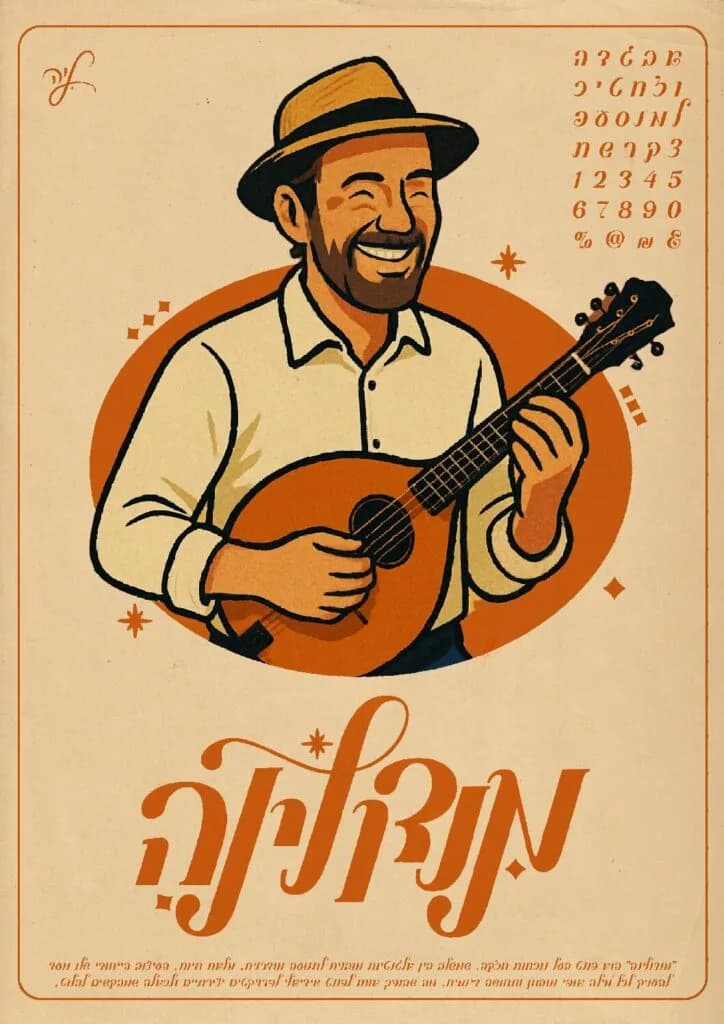
מנדּולינָה טיפוגרפיה דינמית עם אופי ייחודי - "מנדולינה" הוא פונט בעל נוכחות חזקה, שמשלב בין אלגנטיות מובנית לתנועה מודרנית, מלאת חיות. העיצוב הייחודי שלו נועד להעניק לכל מילה אופי מובחן ותחושה דינמית, מה שהופך אותו לפונט אידיאלי לפרויקטים יצירתיים ולכאלה שמבקשים לבלוט. הוא מתאים במיוחד לכותרות ולשמות מותגים שרוצים לייצר רושם יוקרתי אך נגיש, מעניק תחושת תנועה והדגשה להזמנות, תפריטים ומיתוג פרימיום, ומשתלב היטב עם עולמות האופנה והלייפסטייל, כמו מגזינים, לוגואים למותגי יוקרה, אריזות מוצרים וטיפוגרפיה מעוצבת. הפונט נותן טוויסט ייחודי לכל טקסט שדורש גישה לא שגרתית – פוסטרים אומנותיים, קמפיינים יצירתיים, כותרות עם נוכחות, ועיצובים שמשדרים אנרגיה וסגנון מובהק. "מנדולינה" הוא פונט שלא משאיר מקום לאדישות – הוא מביא תנועה, חיות וייחודיות לכל פרויקט, ומעניק לטקסטים אופי מודרני ומובחן. אניטה